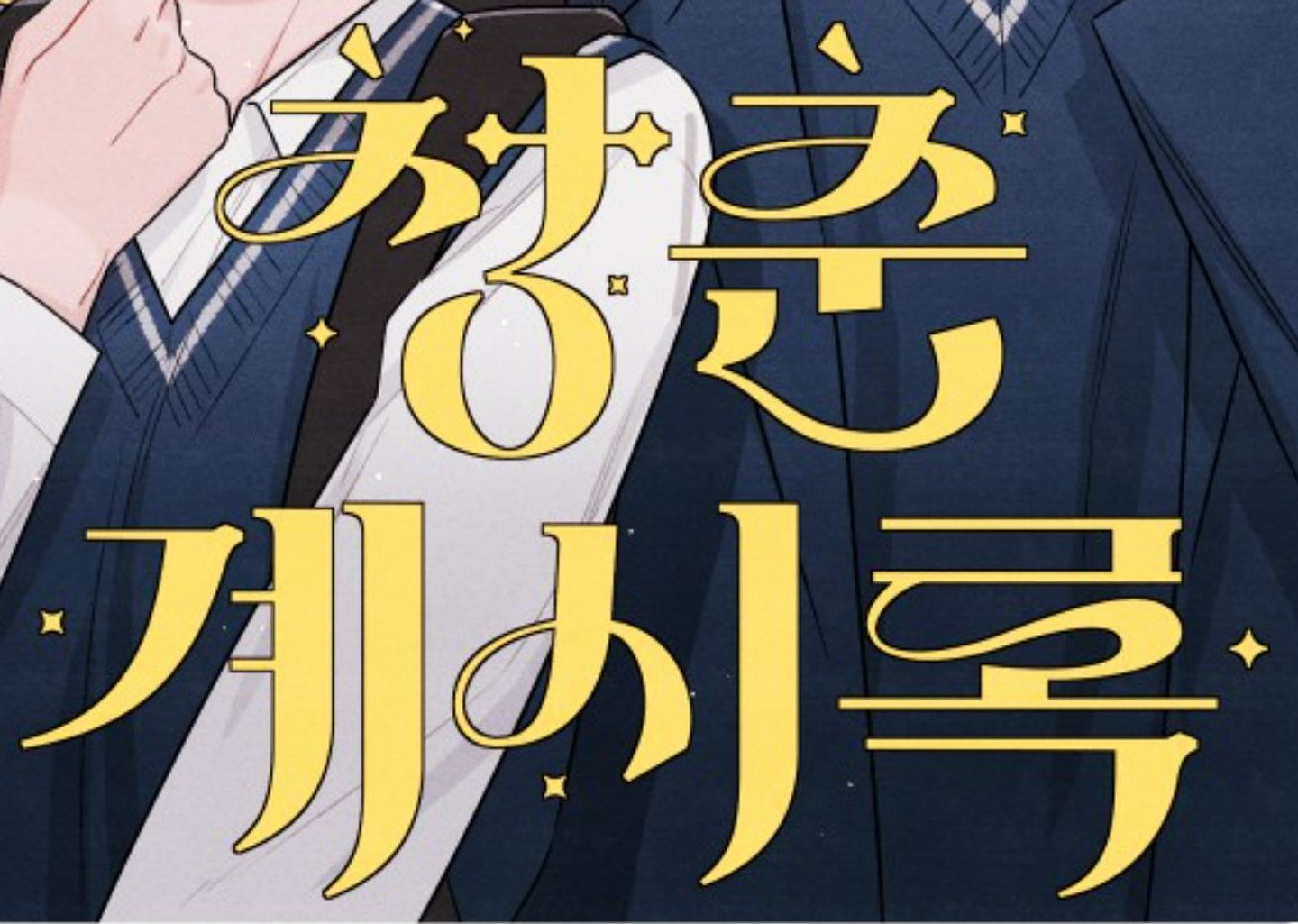
한서 작가님의 웹툰 <청춘계시록> 타이틀 폰트가 궁금합니다! 이런 폰트가 없다는 얘기를 듣긴 했는데 변형해서 만든 타이틀일까요? 만약 그렇다면 어떤 폰트를 변형한 건지 알려주시면 감사하겠습니다:D
HS봄바람체 3.0 토끼네활자공장
웹툰과 웹소설 제목의 경우 일러스트 등을 통한 타이포 작업이 기본으로 이루어지며, 폰트를 찾아드리는 입장에선 어떤 폰트를 변형했는지는 작업자가 아닌 이상 알아보기는 힘듭니다. ^^; 다만 명조 베이스는 걸어드린 폰트와 유사할 것 같으므로 비슷한 형태 원하시면 해당 폰트 베이스로 진행해 보세요.